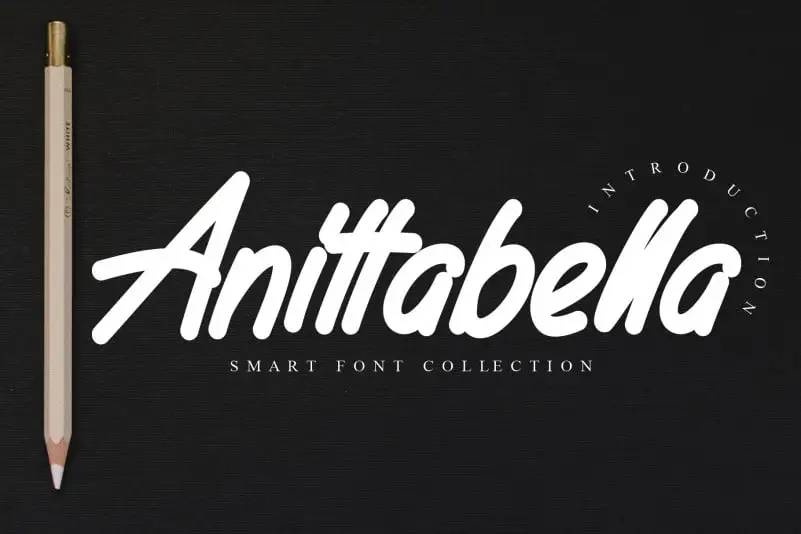
Anittabella Handwritten Font – Fonte Grátis
Anittabella Handwritten Font
A fonte Anittabella Handwritten é uma criação do designer creativeletter que transmite conforto e autenticidade à qualquer projeto para o qual é usada. Seu estilo fluido e quase natural cai perfeitamente sobre textos, tornando-os emocionalmente agradáveis ao leitor. Essa fonte foi projetada para aqueles buscando uma mistura suave entre elegância e casualidade, especialmente útil para aplicativos como redes sociais, sites pessoais ou design de gráficos digitais que desejam transmitir um toque amigável e único. Para quem busca expressar um pouco da personalidade por trás do projeto, Anittabella Handwritten é uma escolha ótima. Seu traçado delicado e detalhado reflete uma voz única, tornando-a perfeita para textos pessoais ou mensagens de texto que buscam dar um toque especial às palavras escritas. Com esse design artesanal, a fonte Anittabella Handwritten não apenas adiciona beleza à sua criação, mas também permite expressar uma essência única e autêntica.